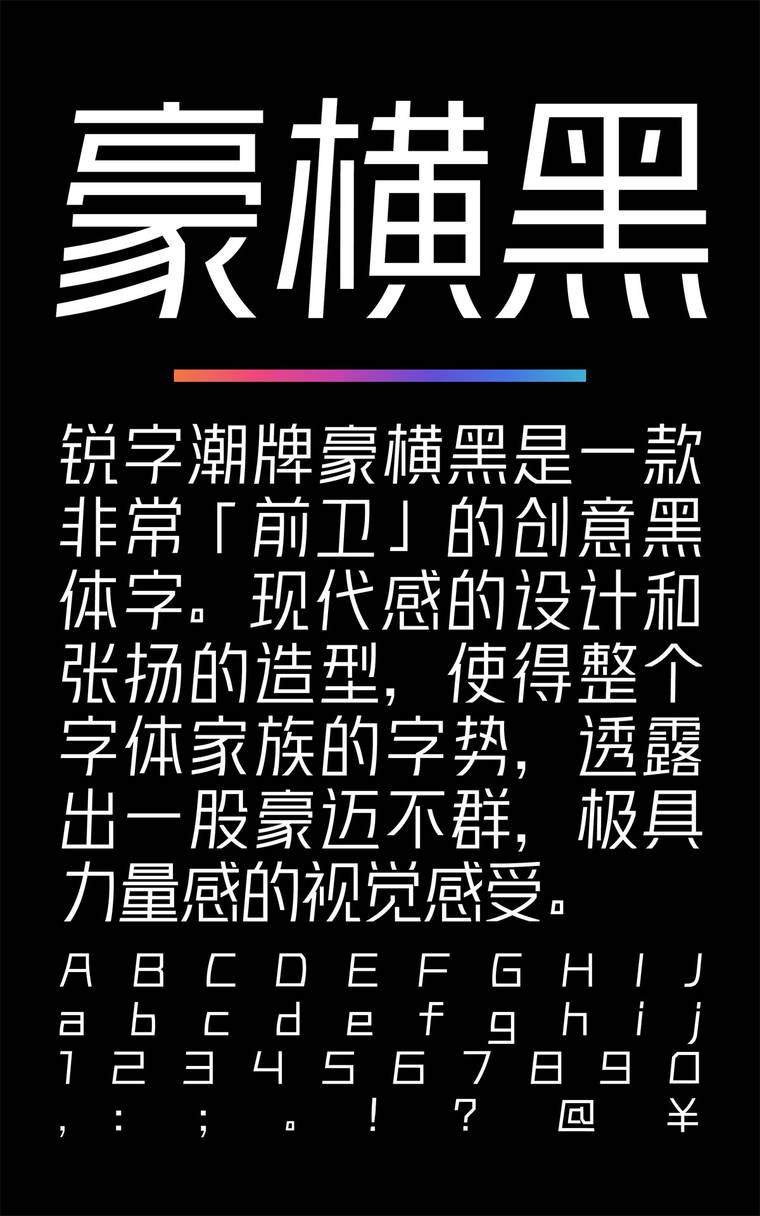
锐字潮牌豪横黑简 常规
锐字潮牌豪横黑简 常规字体介绍
特征描述:这是一款非常有创意的黑体字。融合了斜体字与正体字的独特设计,在笔画上特殊处理,既增加了弧度,又有坚硬的棱角,使字体非常有力量感。尤其是最粗的超黑字重,做了非常多的结构优化,整体的视觉统一性更好,而且在显示环境与视觉场景上也更舒服,适用范围也更广。